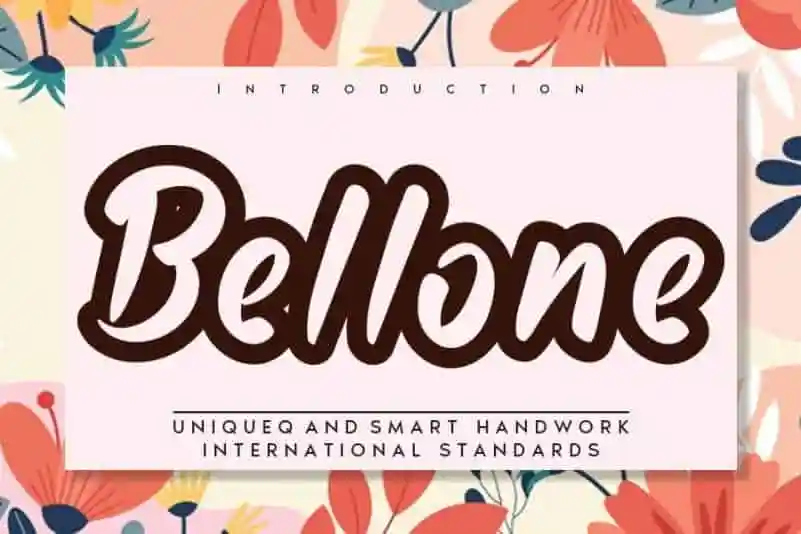
Bellone Display Font – Download Grátis
A Bellone Display Font é uma fonte captafe especialmente projetada para criar impressões memoráveis e únicas. Suas linhas elegantes e acentos suaves conferem um ar casual e autêntico, fazendo com que seja perfeitamente legível e adaptável a diversas usinas de texto. Perfeito tanto para enquadramentos ricos quanto como grande título isolado, a Bellone traz uma dinâmica poderosa que pode ser facilmente aplicada ao seu design. Suas características elegantes e sua versatilidade tornam essa fonte uma escolha ideal para qualquer projeto visual exigente.